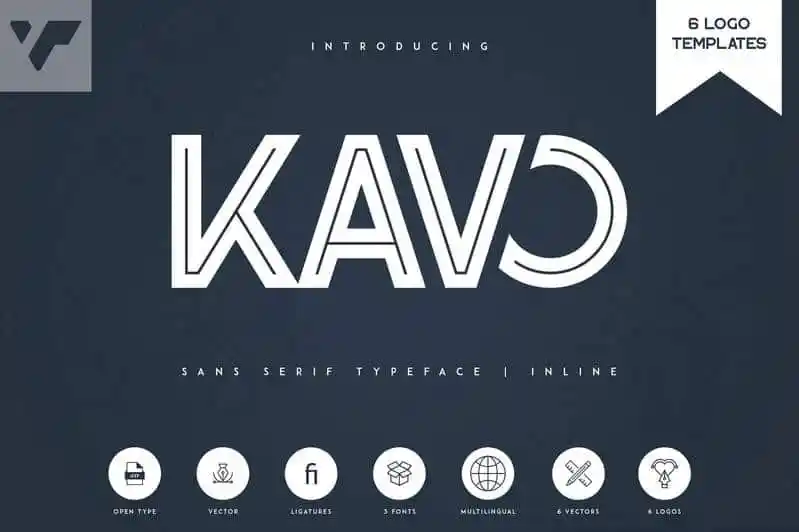
Kavo Inline Typeface – 3 weight + 6 Logo Templates – Fonte Grátis
Kavo Inline Typeface - 3 weight + 6 Logo Templates
A Kavo Inline Typeface é uma elegante e moderna fonte de linhas curvas com 3 pesos, ligaduras, seis desenhos vectoriais únicos, seis moldes de logomarcas e suporte multilíngue. Ela combina perfeitamente para trabalhos em grandes tamanhos e também se destaca em designs menores. Ideal tanto para uso em design gráfico profissional quanto para criação de logotipos personalizados, a Kavo Inline Typeface oferece um amplo espectro de opções. Esta fonte é certamente uma escolha versátil que não apenas reforça sua presença visual, mas também se adapta à sua necessidade específica de design. Com o vp_creative_shop como seu criador, você pode esperar a qualidade e as funcionalidades únicas desta fonte moderna.